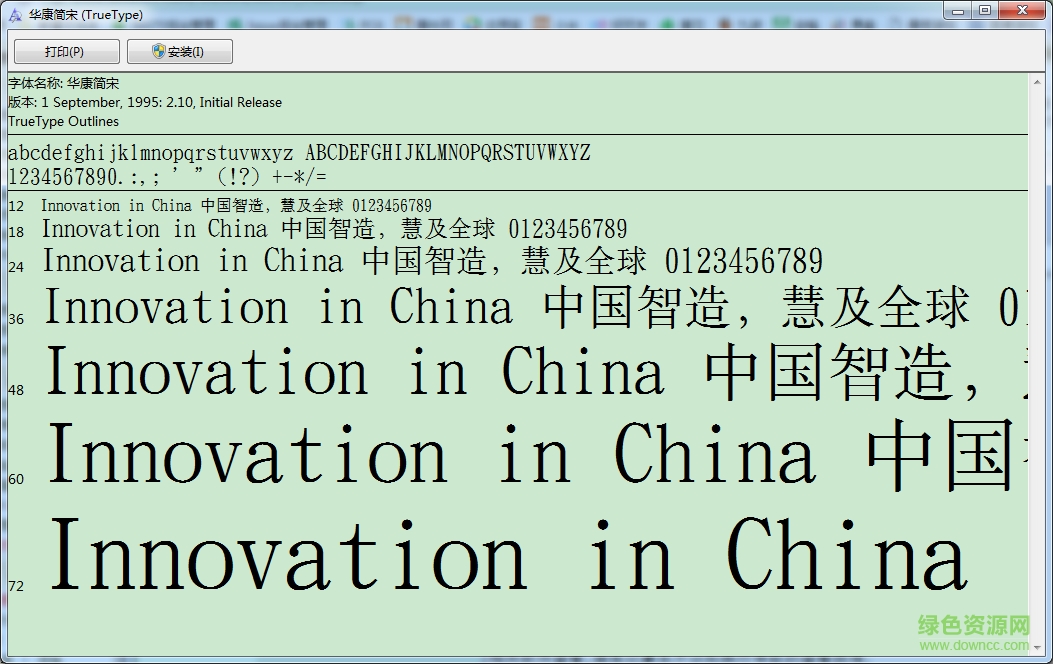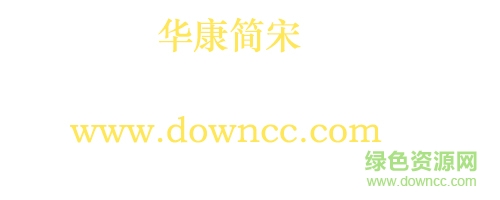
華康簡宋
華康簡宋是一款深受用戶喜歡的簡體宋體字體,這款字體結(jié)構(gòu)清晰,字形端正大方,整體效果非常出色,非常適用于平面設(shè)計、包裝印刷、廣告等領(lǐng)域。需要的朋友不妨來綠色資源網(wǎng)下載體驗吧!
提供了全新選擇。這款字體不想藝術(shù)字體那樣非常的有特色,但是字體工整,字體勻稱,字體方正。有著廣泛的使用價值。常備作為企業(yè)商業(yè)用字。當(dāng)然個人用字也是十分不錯